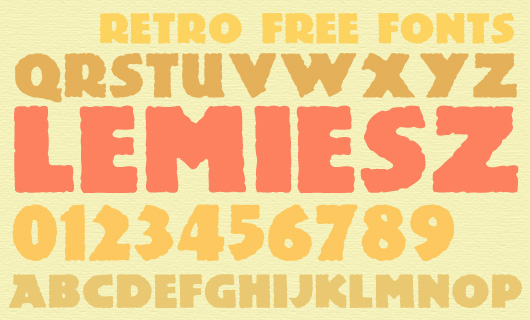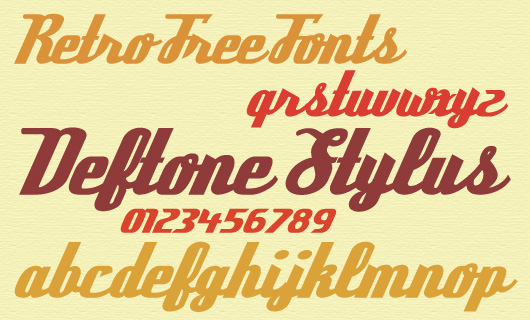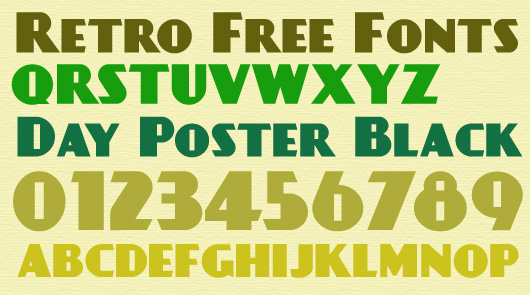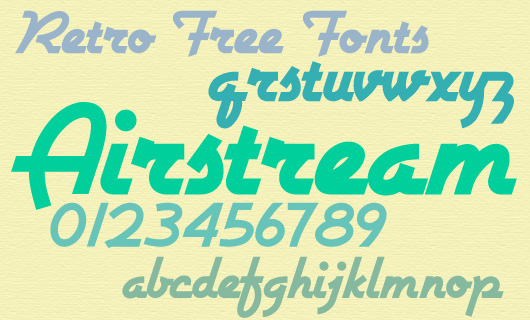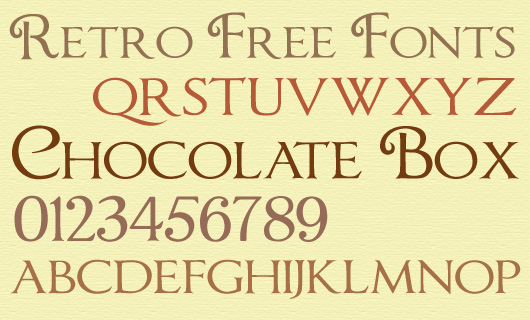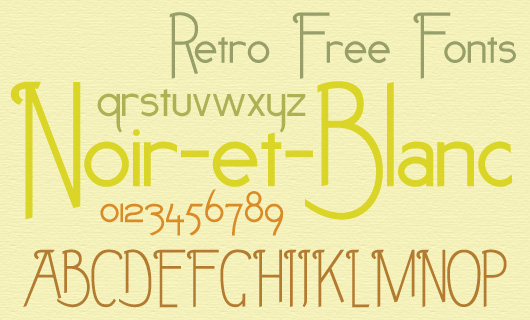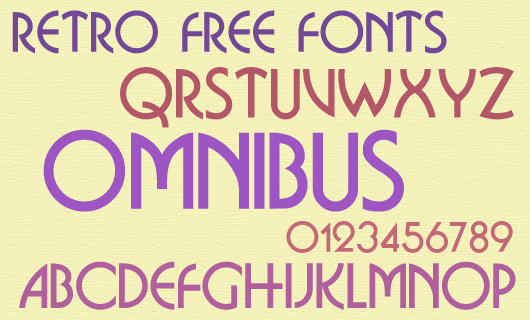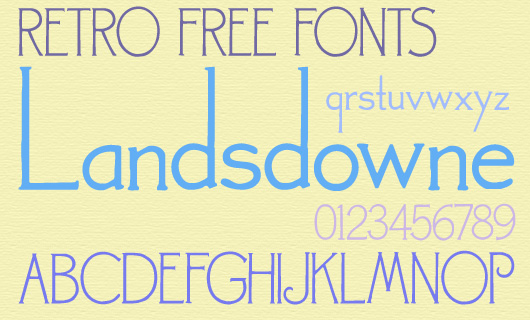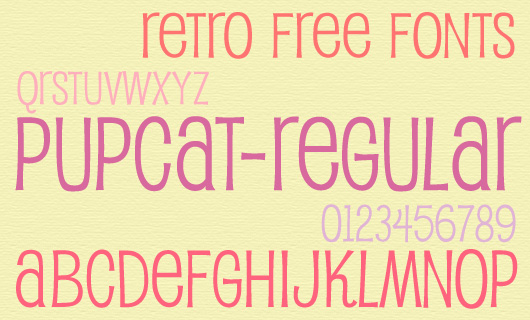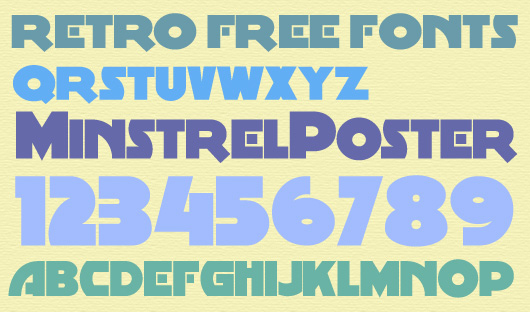
Non-Websafe Fonts als Alternative zu den bekannten Schriften wie Verdana, Arial und Georgia zu verwenden, ist derzeit im Webdesign DER Trend. Und mit neuen Möglichkeiten wie CSS @Font-Face, Cufon oder SIFR wird es auch immer leichter, eine vielseitigere Auswahl von Schriften zu nutzen.
Bei Fontsquirrel oder Dafont gibt jede Menge schöne Free-Fonts, die du für dein nächstes Webdesign verwenden kannst. Ich habe eine kleine Auswahl unsere derzeitigen Lieblings- Retro Free-Fonts zusammen gestellt.
1. Lemiesz
2. Deftone-Stylus
3. DayPosterBlack
4. Airstream
5. Chocolate Box
6. Noir-et-Blanc
7. Omnibus
8. Landsdowne
9. Pupcat
10. MinstrelPoster
Chocolate Box find auch toll! Und Noir-et-Blanc gefällt mir auch.
Eine tolle Sammlung :) Mir gefällt Pupcat am besten. Und bei Chocolate Box finde ich vor allem die Ziffern sehr schön.